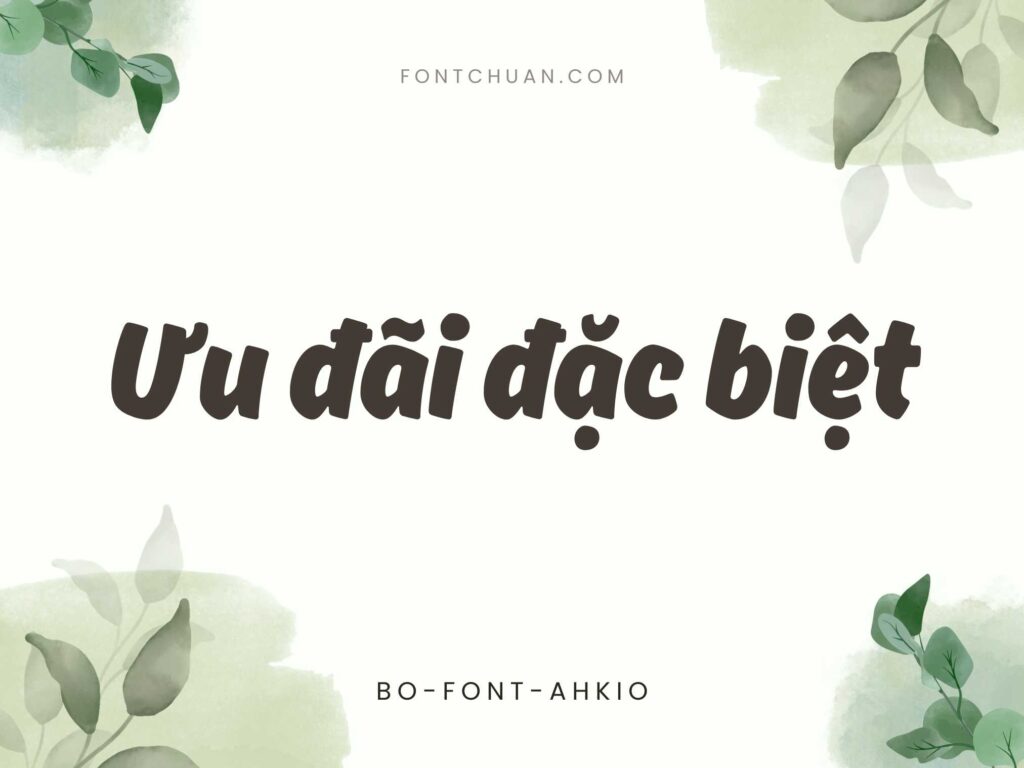
Font FS Ahkio Trọn Bộ Việt Hóa
Ahkio là một bộ font chữ viết tay được thiết kế bởi Mika Melvas, lấy cảm hứng từ nghệ thuật vẽ biển quảng cáo và chữ viết trên bảng hiệu thập niên 1930, nhưng mang phong cách hiện đại và độc đáo. Với các đường nét mềm mại, bo tròn và thân chữ hơi cong, Ahkio tạo cảm giác thân thiện và nhẹ nhàng, phù hợp cho các tiêu đề, bao bì, logo và poster. Bộ font bao gồm 5 trọng lượng, giúp tăng tính linh hoạt và tạo sự tương phản trong thiết kế. Nhờ sự Việt hóa của Phông Chữ Việt, Ahkio hỗ trợ đầy đủ các ký tự tiếng Việt, đáp ứng nhu cầu thiết kế đa ngôn ngữ. Thành viên của Font Chuẩn đã sưu tầm và chia sẻ font này để phục vụ cộng đồng thiết kế.
Về đặc điểm thiết kế, Ahkio nổi bật với các nét cọ rời rạc, mang lại cảm giác tự nhiên và phóng khoáng. Font cung cấp đầy đủ chữ hoa, chữ thường, số và các ký tự đặc biệt, cùng với hỗ trợ đa ngôn ngữ. Đặc biệt, Ahkio còn bao gồm các ký hiệu “manicule” đen trắng, dễ dàng sử dụng thông qua các tùy chọn OpenType. Font này lý tưởng cho các dự án thiết kế như thiệp mời, poster sự kiện, bao bì sản phẩm và các ấn phẩm quảng cáo. Ngoài ra, Ahkio cũng phù hợp cho các sự kiện như lễ hội, sinh nhật, Valentine và Trung thu, mang lại không khí ấm áp và gần gũi. Trong lĩnh vực ngành nghề, Ahkio được ứng dụng rộng rãi trong quảng cáo, thiết kế đồ họa, giáo dục và công nghệ, góp phần tạo nên sự độc đáo và thu hút cho các sản phẩm và thương hiệu.